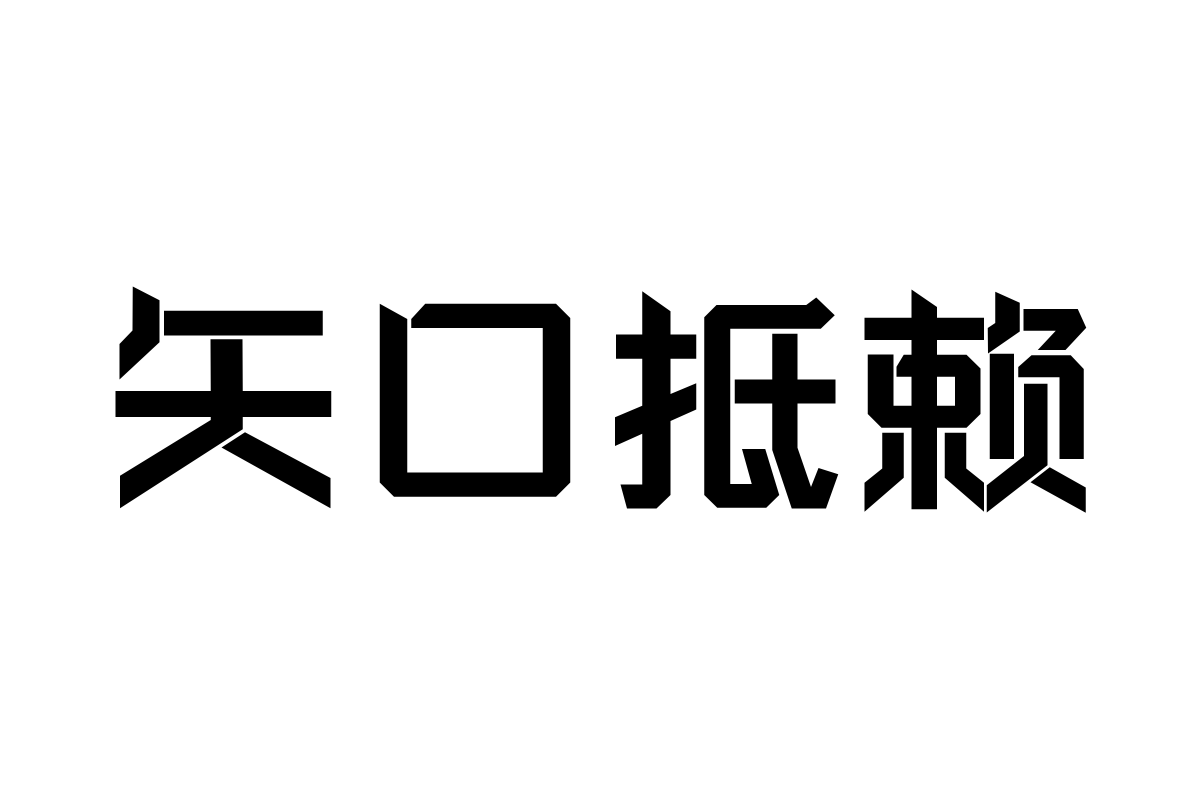
三极芯片体粗字体是一种较为粗壮的字体,其特点是笔画粗大,线条清晰。这种字体通常用于需要强调和突出显示的文字,如标题、广告、标志等。它的特点是易于阅读和识别,同时也具有较强的视觉冲击力。
在设计中,三极芯片体粗字体可以用于吸引观众的注意力,传达出强烈的信息和情感。它的应用范围非常广泛,包括广告、标识、报纸、杂志、书籍、网页等。
总的来说,三极芯片体粗字体是一种实用且有效的字体选择,它可以帮助你更好地传达你的想法和信息。